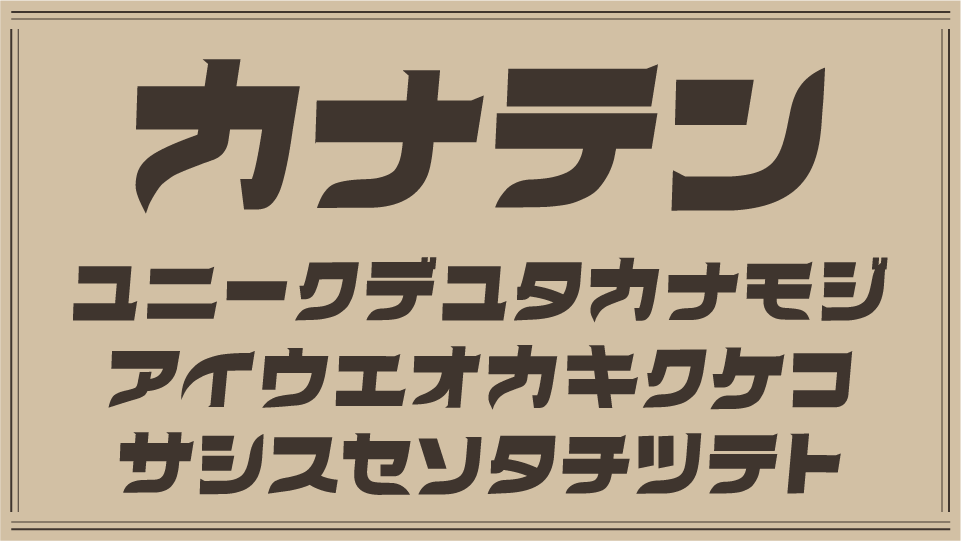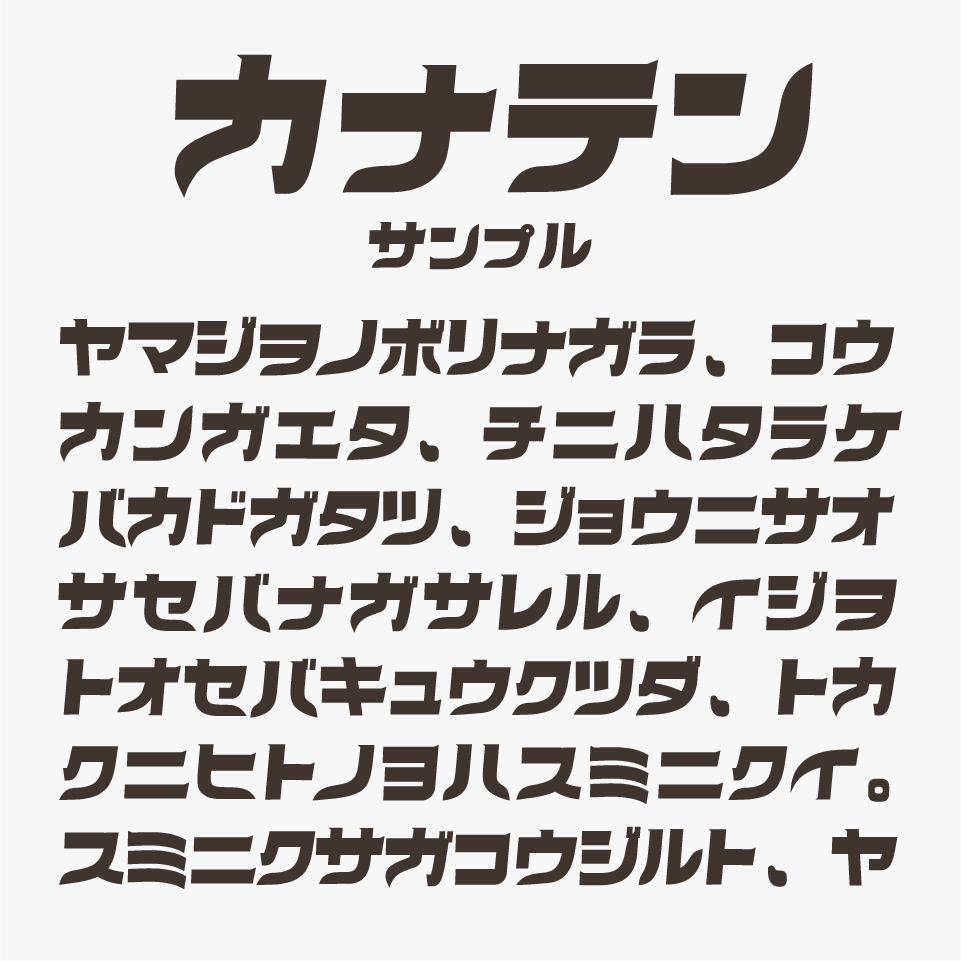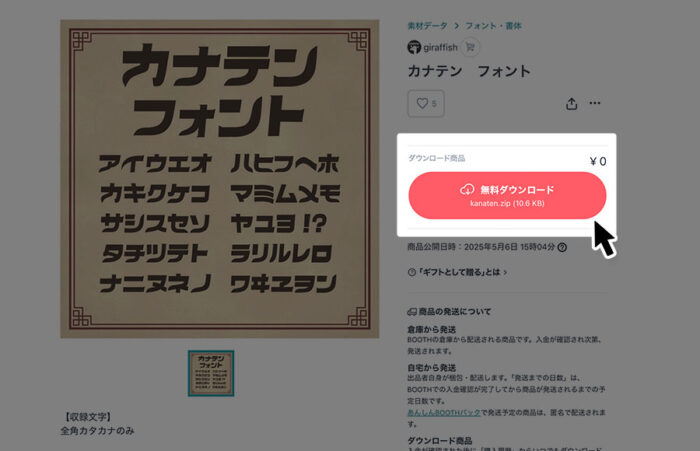
カナテン
カナテンフォントは、斜体のフォルムに、シュッっとした勢いのあるデザインが特徴的のカタカナフォントです。
筆文字のようなうねりや勢いをもち、スピード感を感じる表情があるデザインとなっています。純喫茶の店名や昭和歌謡の映像作品を思わせるようなレトロな佇まいも感じるフォントとなっています。
収録文字は、カタカナが収録されています。